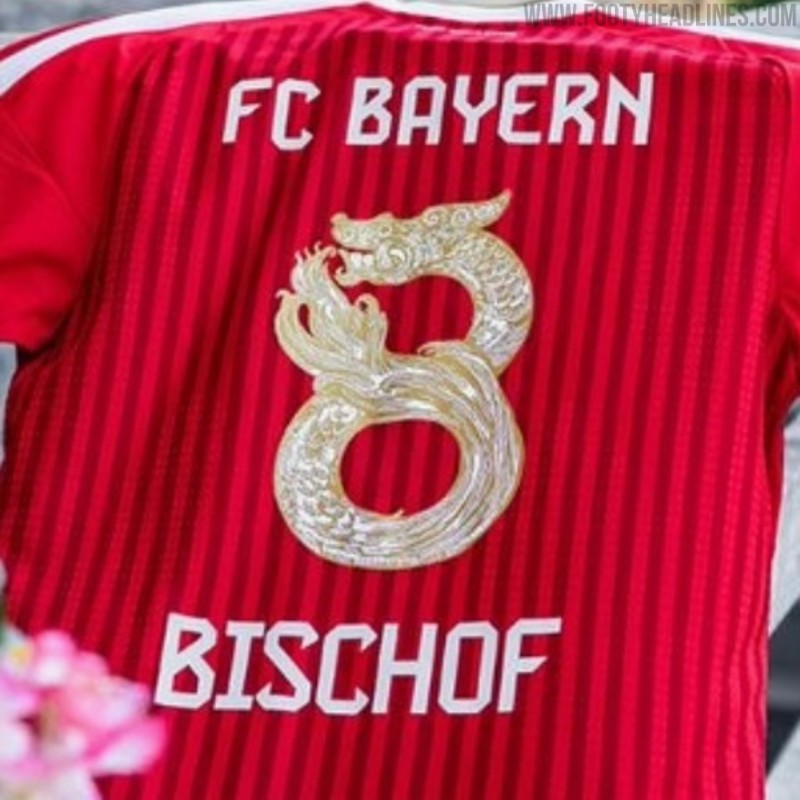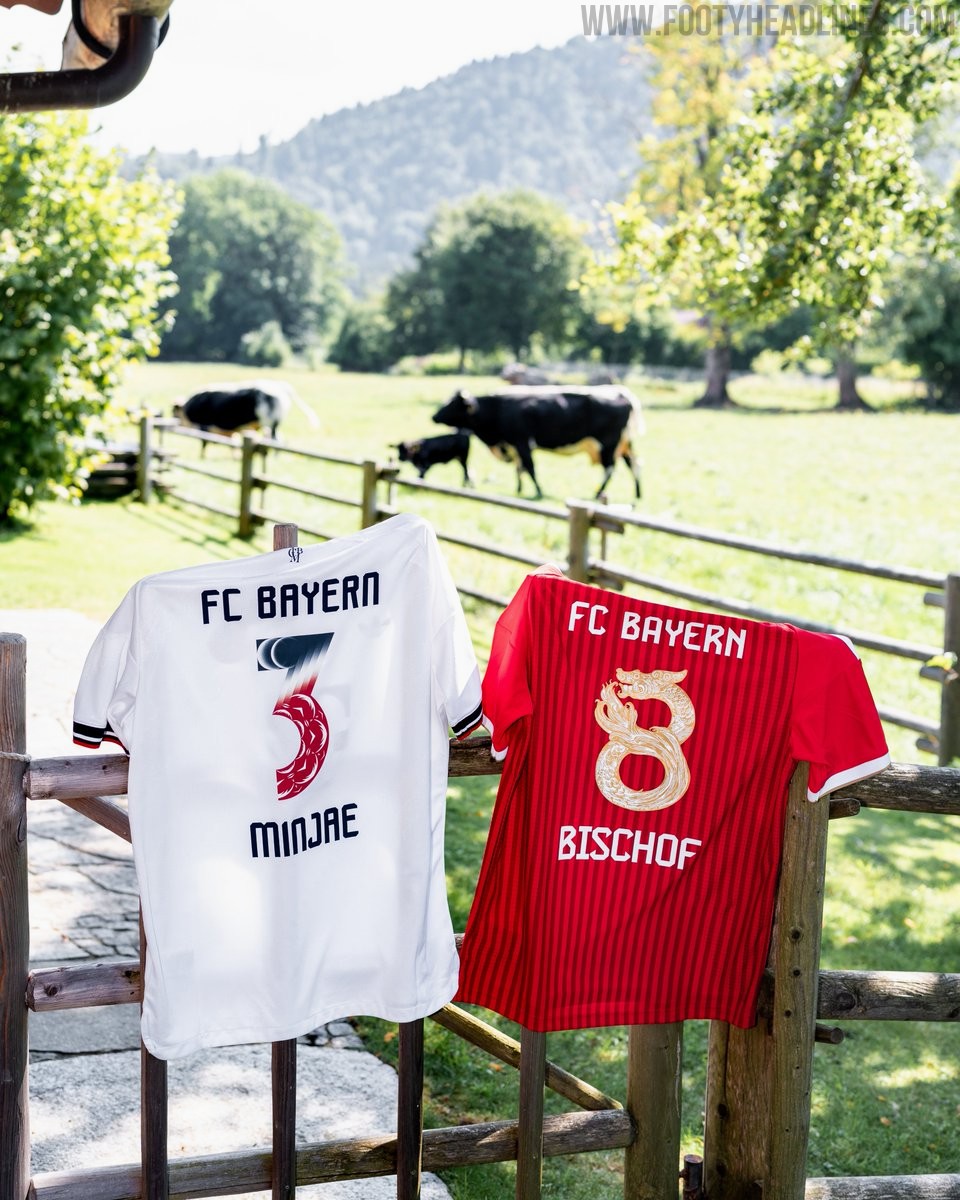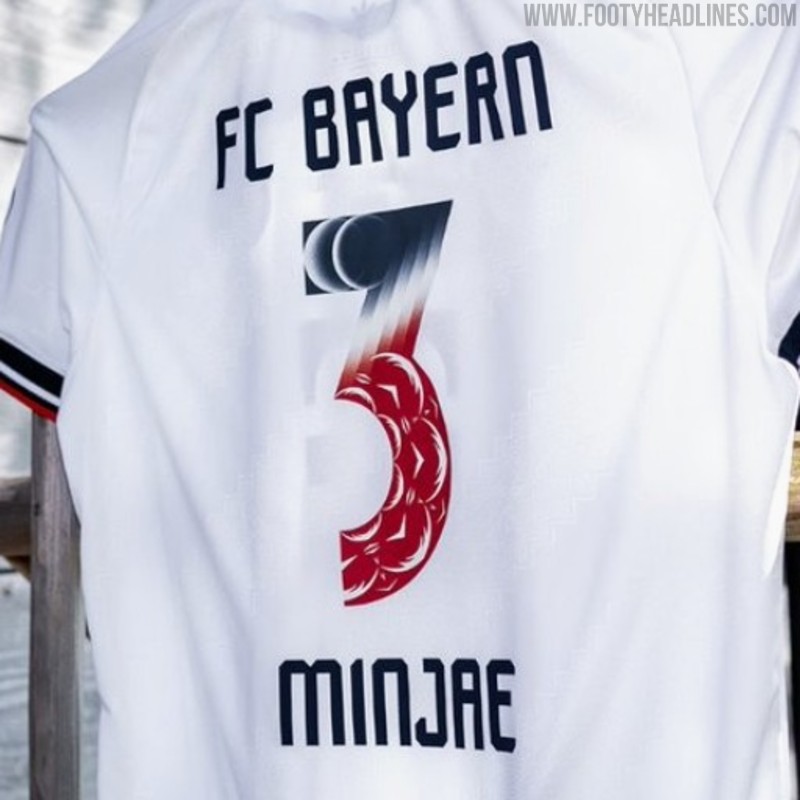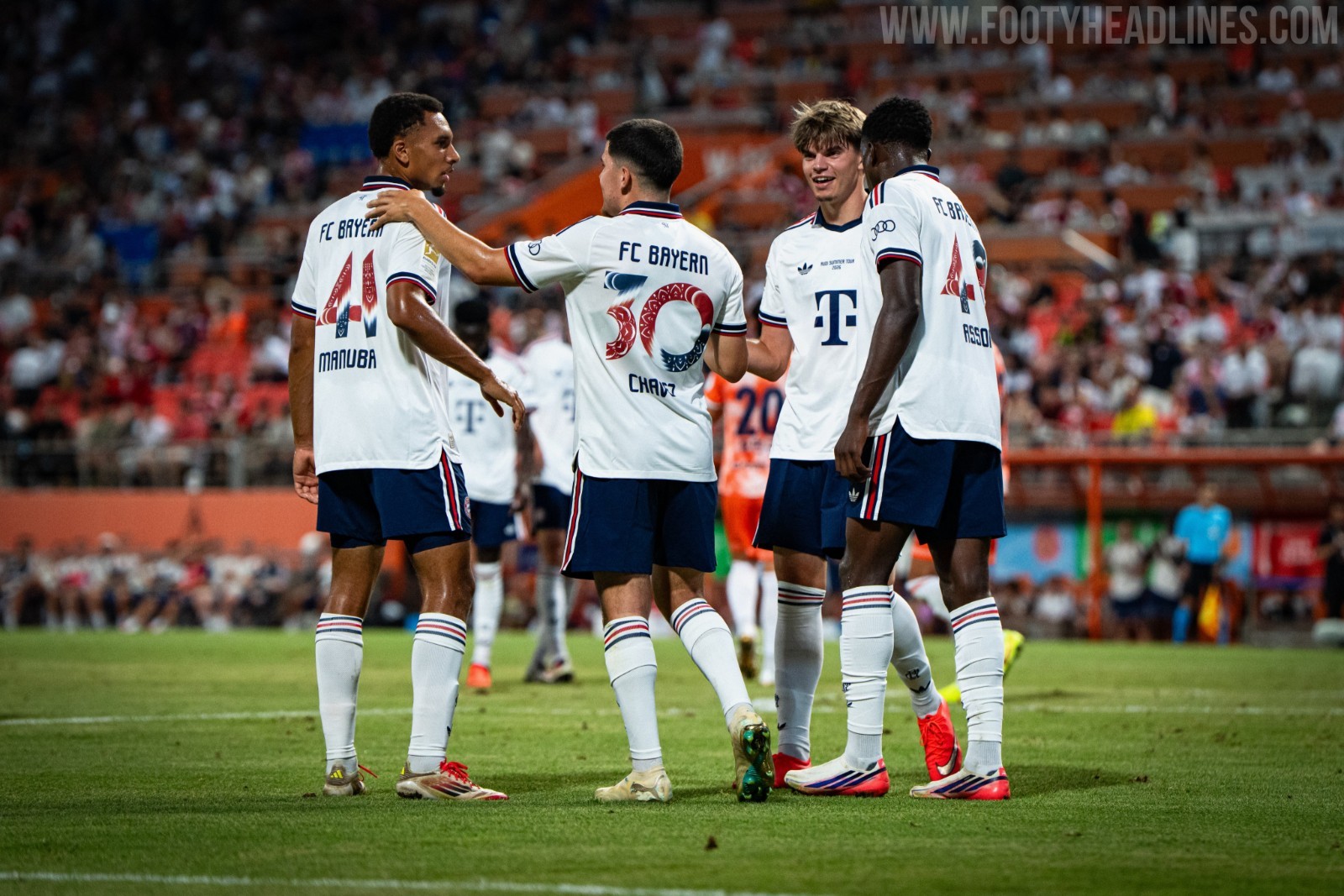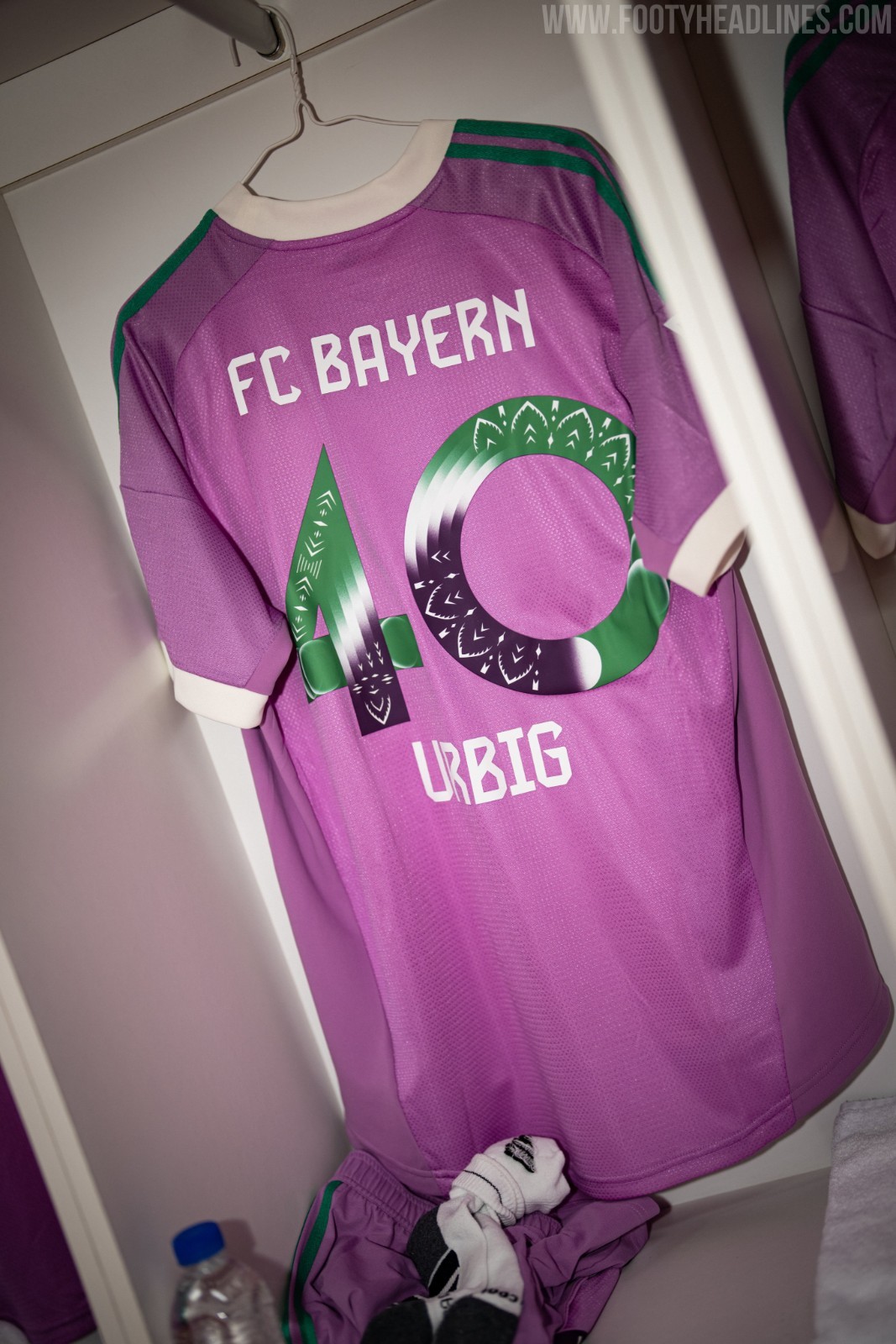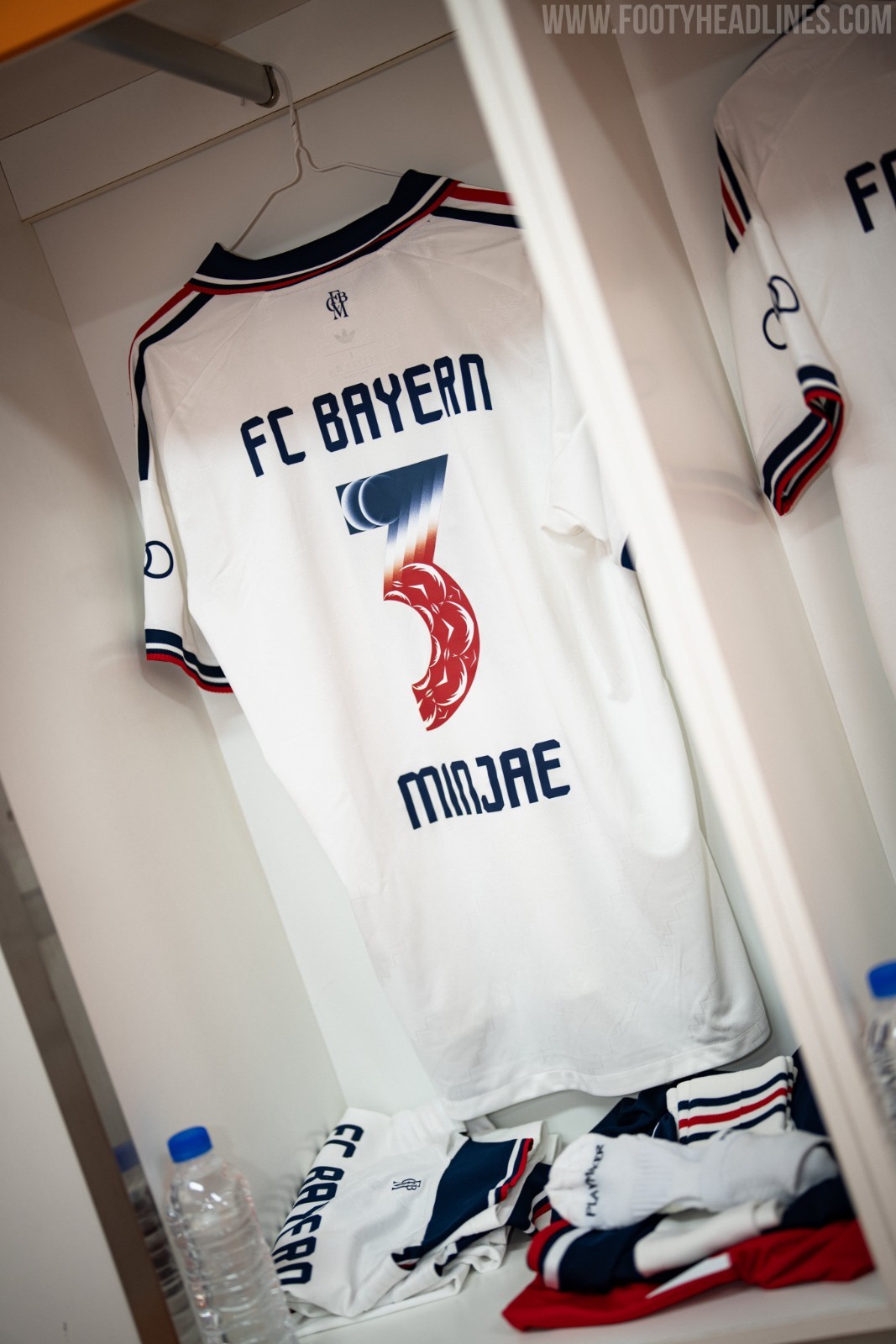
Spezielle Bayern-München-Trikot-Schriftarten für die Freundschaftsspiele in Asien veröffentlicht
• Anlass der Schriftart-Veröffentlichung: Der FC Bayern München hat spezielle Trikot-Schriftarten für seine bevorstehenden Freundschaftsspiele im Rahmen der Audi Summer Tour in Asien veröffentlicht.
• Kulturelle Design-Inspiration: Die individuellen Schriftarten wurden in Zusammenarbeit mit Hypebeast und adidas entworfen und sind von lokaler Kunst und traditioneller Kultur aus Jeju und Hongkong inspiriert.
Update – Donnerstag, 5. August 2026: Bayern München hat die spezielle Schriftart für das Auswärtstrikot im Vorbereitungsspiel gegen Jeju SK FC zum ersten Mal präsentiert. Außerdem gibt’s einen Blick auf die spezielle Schriftart für die Torwarttrikots. Leider ist die spezielle Schriftart nur vor Ort in Südkorea erhältlich.
Spezielle Bayern-München-Trikot-Schriftarten für die Freundschaftsspiele in Asien veröffentlicht
Der FC Bayern München hat die individuell gestalteten Trikots für seine bevorstehenden Freundschaftsspiele in Asien während der Saisonvorbereitungstour vom 26. bis 27. vorgestellt. Die in Zusammenarbeit mit Hypebeast und adidas entworfenen, maßgeschneiderten Namen und Rückennummern werden bei den Spielen der Audi Summer Tour des deutschen Vereins auf der südkoreanischen Insel Jeju und in Hongkong getragen.
Jedes Trikot hat eine einzigartige Eigenschaft: ein Schriftdesign, das in der lokalen Kunst und traditionellen Kultur verwurzelt ist. Für das Spiel auf Jeju hat die koreanische Künstlerin Dohee Khwon das Design an „Gime“ angelehnt – eine traditionelle Papierkunst, die es nur auf der Insel Jeju gibt und die mit lokalen Ritualen verbunden ist. Dabei hat sie subtile Sonnen- und Mondmotive in die Rückennummern eingearbeitet. Für das Spiel in Hongkong im Kai Tak Stadium hat der lokale Künstler Kristopher Ho eine kunstvolle goldene Drachengrafik entworfen, die in die Rückennummern eingewoben ist und sich an der alten chinesischen Ästhetik orientiert.